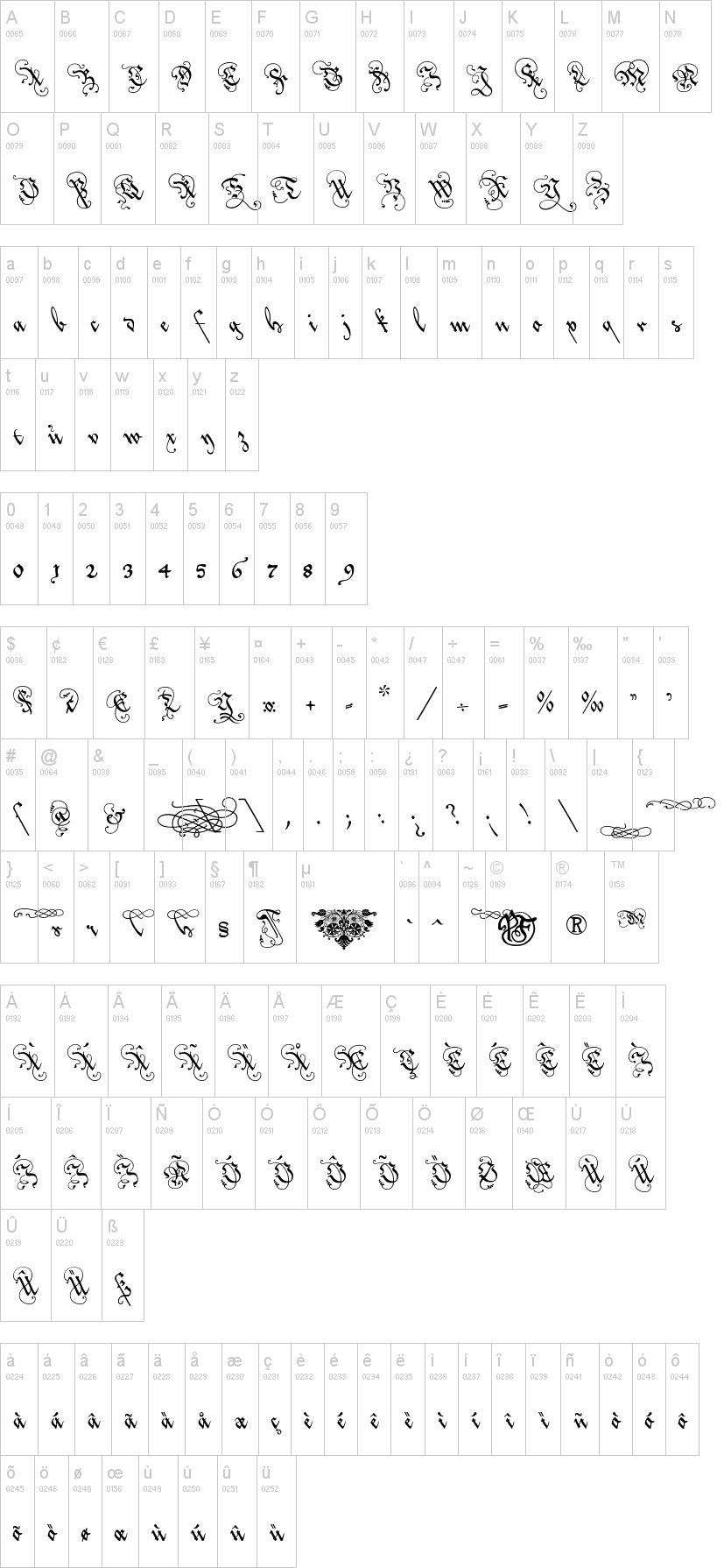
Loves Labour是一种古典风格的手写字体,它的特点是优美而优雅的笔画,适用于印刷或手写风格的设计项目。该字体具有一些独特的特征,例如斜体字母有一定的厚度和弯曲度,使其看起来更加自然。 Loves Labour字体设计师Lucas Sharp描述说,该字体是基于印刷术发明的时期创作的,它包含了该时期的一些经典元素,但也加入了一些现代的风格元素。这使得Loves Labour字体既有古典的感觉,又不失现代感。 Loves Labour字体适用于各种印刷和设计项目,如海报、卡片、传单、标志和网站设计等。它可以用于表达传统、温暖和亲切的感觉,也可以用于表达现代、时尚和优雅的感觉。内容介绍
Loves Labour是一款非常不错的手写艺术字体,具有很好的视觉感,适合于文化类的宣传设计、商业类品牌的广告和产品包装设计以及个性化文字排版等较多场景。